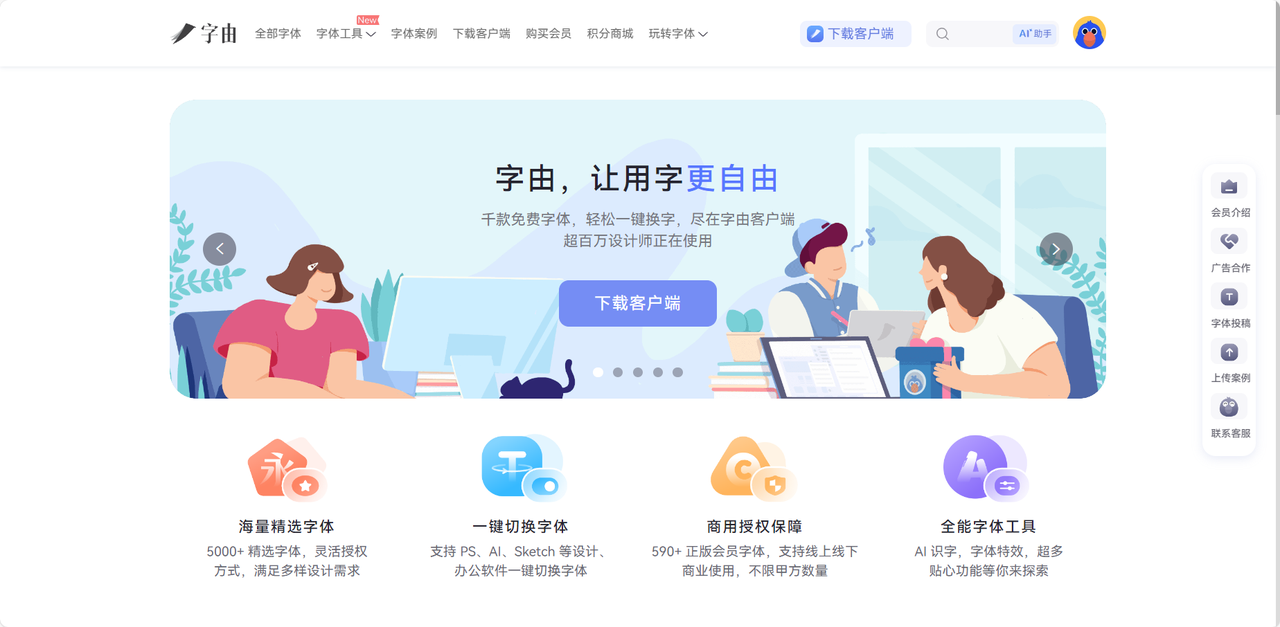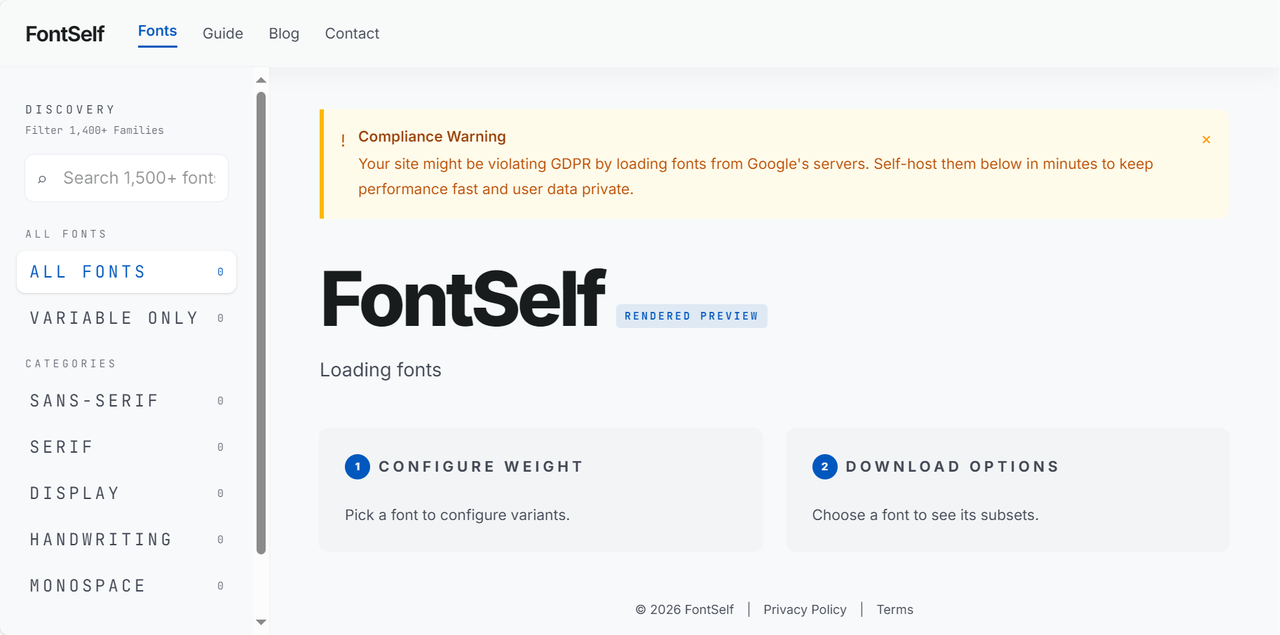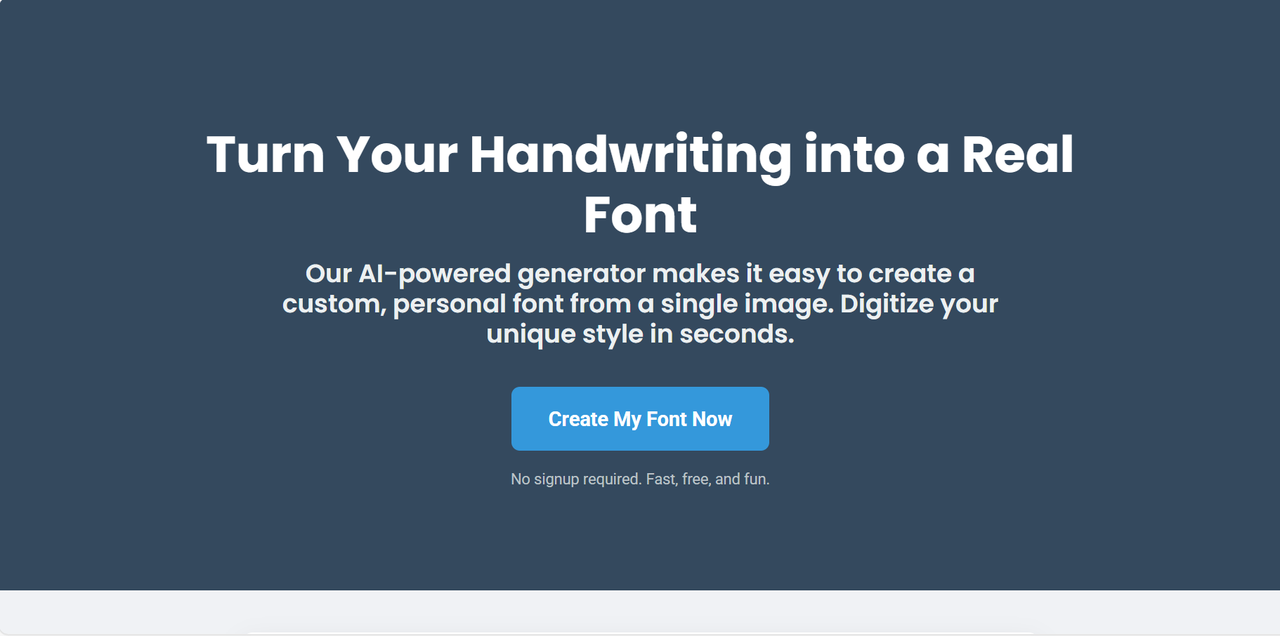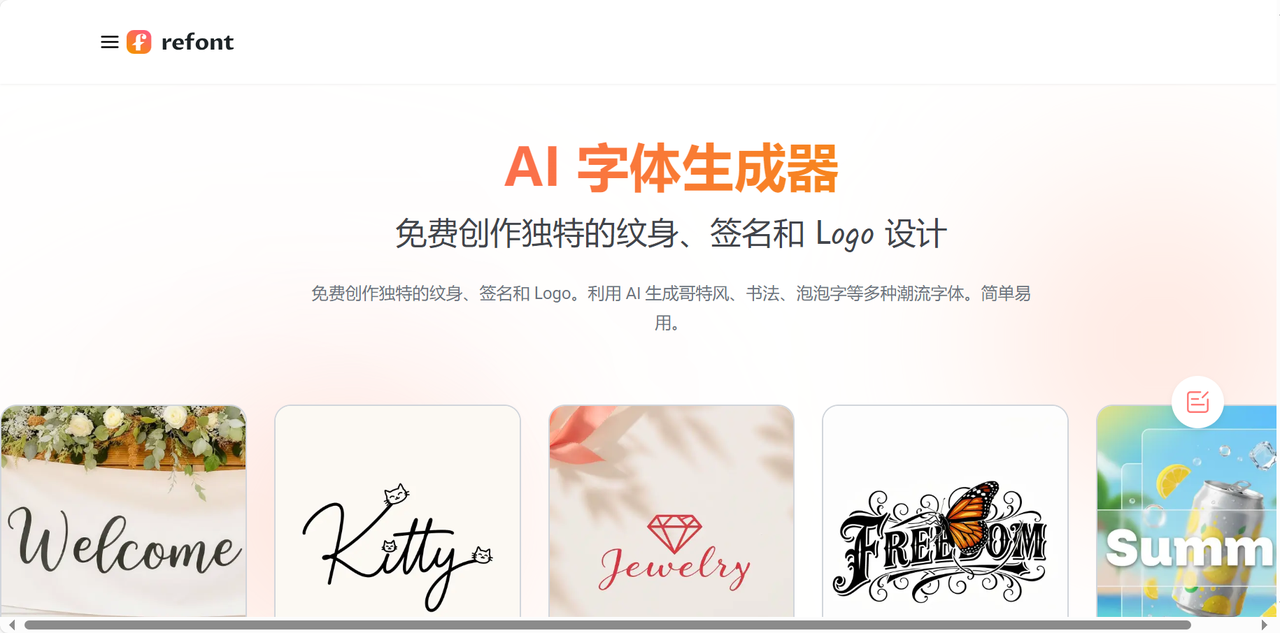
记住这几个设计师必备工具,堪称字体美化大师
在设计行业,字体是非常重要的存在,总觉得字体平平无奇,想要美化又无从下手?不会用专业的字体设计软件,找其他辅助工具又一堆广告,拖慢整体的设计进度。别急!我这就给大家推荐几个设计师必备的工具,每一个都堪称是字体美化大师,不管是一键生成创意字体还是增添字体效果,这些工具都能满足你。选择一个合适的字体美化工具,不仅能帮你把普通文字变成设计亮点,打造专业级的字体效果,还能提升作品的视觉冲击力和质感格调,让你的设计之路更加顺畅!
一、字由
提起字体美化工具,字由一定是我的首选。它是目前国内设计师使用频率最高的字体管理工具,核心优势就在于海量正版字体库一键激活和 AI 工具在线生成艺术字体,是名副其实的字体美化大师。
先说字体资源,字由涵盖了黑体、宋体、圆体、书法体、楷体、手写体、创意字体等多种字体风格,覆盖所有设计场景。其中会员商用字体 590+ 款,免费商用字体 3590+ 款,单独授权字体 5120+ 款,每款字体资源左上角都表明了授权类型,便于用户选择,保证你用字无忧。最关键的一点是,字由改变了“找字体、下载字体文件、安装字体”这一套繁琐的步骤,通过字由客户端可实现在 PS、AI、ID、XD、Figma、Sketch、CDR 等设计软件中一键应用字体,无需下载,安装字体包,非常方便。
再说 AI 工具,字由内置的 AI 字体生成功能,本质上就是一个很好用的在线艺术字转换器。用户只需要选择一个心仪的模板,输入文字内容,30s 之内就可以获得同款艺术字,很适合偏爱创意设计的小伙伴们,轻轻松松完成字体美化。生成的字体直接下载为透明背景的 PNG 图片,直接拖进 PS、剪映或者海报设计稿里,即拖即用。
二、Fontself Maker
Fontself Maker 是一款很特别的字体美化工具,和前面提到的字由不同,它不提供现成的字体资源,而是可以帮助你在 Photoshop 和 Illustrator 里亲手创造出属于你自己的字体。对于需要为品牌或者个人 IP 定制专属字体的资深设计师来说,这个工具简直是必不可少的,完美优化了设计一套字体的时间成本。它的操作逻辑非常简单,你只需要在 AI 或 PS 里绘制好字母、数字、常用标点符号等,选中所有字符拖拽到 Fontself Maker 的面板里,它会自动生成一个专业格式的字体文件。
我觉得 Fontself Maker 最大的亮点就是支持创建彩色矢量字体,你可以为每个字符添加渐变、图案等多种效果,从而打造风格独特且醒目的标题字。另外,该工具可以在线转换现有字体的不同风格,比如你自己的手写字体上传到 Fontself Maker 以后,可以将它转化为数字字体、像素风字体等多种类型,这样就可以应用于多种网页设计当中啦,方便且快捷。如果你追求个性化的文字美化,不喜欢直接套用别人的字体,希望自己的作品能有一套独一无二的风格,Fontself Maker 绝对是值得入手的工具!
三、Handfonted
有些品牌设计师经常会觉得电脑里的字体过于冰冷,想要一些带有人情味的手写风字体,想要自己写一段文字但又不能输入,Handfonted 就完美解决了这一痛点,它是一个 AI 字体生成器,可以将你的手写字变成真正的可以在电脑上安装并使用的可输入字体文件。
用户只需要去官网下载或打印 Handfonted 提供的模板,在模板内填入对应的字符,然后拍照或扫描上传,内置的 AI 模型会自动检测字符的轮廓,从而生成一款和自己的手写笔迹一模一样的字体文件。不过这也比较考验用户的书写能力,写字不好的小伙伴可以尝试别的字体美化工具哈。我之前尝试过一次,Handfonted 几乎可以还原书写文字时的笔墨浓淡及连笔效果,看上去很有温度感和真实感。
Handfonted 目前支持英文字母和基本符号的输入,整个流程完全在线操作,不需要下载软件,前期可以免费试用,如果你觉得好用,后期可以选择付费哦。该工具非常适用于儿童绘本、婚礼请柬设计、生活类品牌设计等场景,字体本身就是承载设计师故事的一种媒介,用它生成的真实手写风字体更能展现出亲和力和人情上的温暖气息,能为你的作品打造出不一样的意义。
四、Refont AI
Refont AI 是一个快速生成签名字体、书法字体、手写字体或花式字体的字体生成器,和字由类似,它不需要你掌握任何的设计技巧,也不需要自己绘制或者书写任何字符,对新手小白超级友好!Refont AI 不仅字体风格多,而且设计都比较独特,能为你的作品增添不一样的色彩。用户可以直接在输入框写下自己想要的文字,几秒钟后就能看到几十种不同风格字体的预览效果,比如随性的手写体、流畅自然的签名体、艺术感满满的装饰体、活泼的卡通体等等,选中喜欢的风格,下载后就可以应用于你的作品了。Refont AI 支持将文字下载为 PNG、JPG 或 SVG 格式的高分辨率图片,或者是可以安装的字体文件,后续直接放进海报、封面、社交媒体配图或短视频的标题画面里。
值得夸赞的是,Refont AI 在各种风格之间切换自如,不会出现卡顿情况,特别适合那些“高频次、短周期”的设计需求,而且还可以根据设计场景搜索字体。假设你是一个电商设计师,最近处在促销高峰期,每天都要产出多张活动海报,你就可以在 Refont AI 的文本框内输入“爆款直降”“限时促销”类似的字眼,它会自动推荐符合文字风格的字体,挑一个好看的直接应用即可。
以上就是 4 款设计师必备的字体美化工具,每个工具的功能各有千秋,选择适合自己的就可以。字由不仅有海量字体模板能一键激活,还能生成艺术字效果,是比较全面的字体管理平台;Fontself Maker 支持在 AI 和 PS 里直接画字,几分钟生成一套专属字体文件;Handfonted 可以将书面手写笔迹转化为字体文件,打造更有温度的字体;Refont AI 则满足了快速高频生成好看字体效果的需求,免费还门槛低。相信有了这些工具的帮助,字体美化也会变得很简单高效,一起来试试吧!